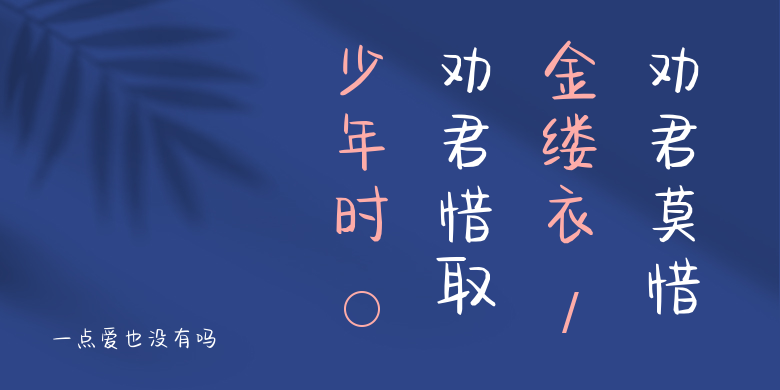
一点爱也没有吗
一点爱也没有吗,这款字体结构工整、笔画清晰,兼顾美观与易读性,适用于标题、正文、海报、包装、LOGO 等多种场景。字形优雅稳定,风格百搭耐看,适配日常排版与创意设计,让文字呈现更舒适、更具质感。一点爱也没有吗一笔一画,皆是细节,以均衡的比例、流畅的线条打造舒适视觉体验,字形端正大气,风格简约现代。无论是商业设计、品牌宣传还是日常排版,都能轻松驾驭,让文字更有格调与力量。一点爱也没有吗字体下载。